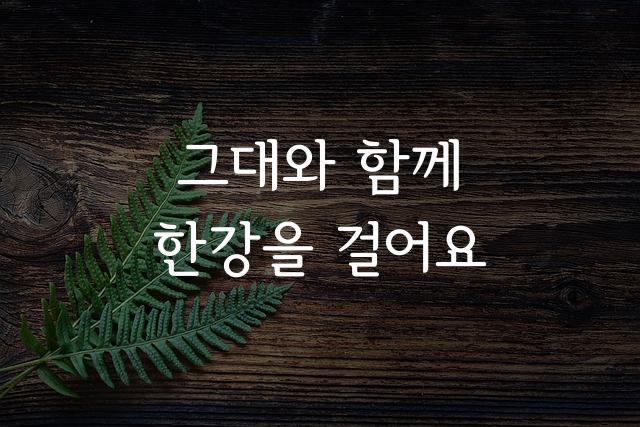
서울남산체는 서울시청에서 제작한 현대적인 고딕체로, 깔끔하고 명확한 선들이 특징입니다. 도시적 감성을 담은 기본 고딕 폰트로서, 모든 종류의 텍스트에 잘 어울립니다.
서울남산체은(는)
기본 고딕, 감성적인, 부드러움 계열의 생김새를 가지고 있으며
웹/앱 디자인, 보고서/문서, 출판물 제목 등에서 자주 활용되며, 효과적인 메시지 전달에 적합합니다.
이 폰트는 출판/미디어, 기술/IT, 금융/비즈니스 분야에 잘 어울리며,
신뢰감, 명확한, 전문적인 느낌을 담고 있는 것이 특징입니다.